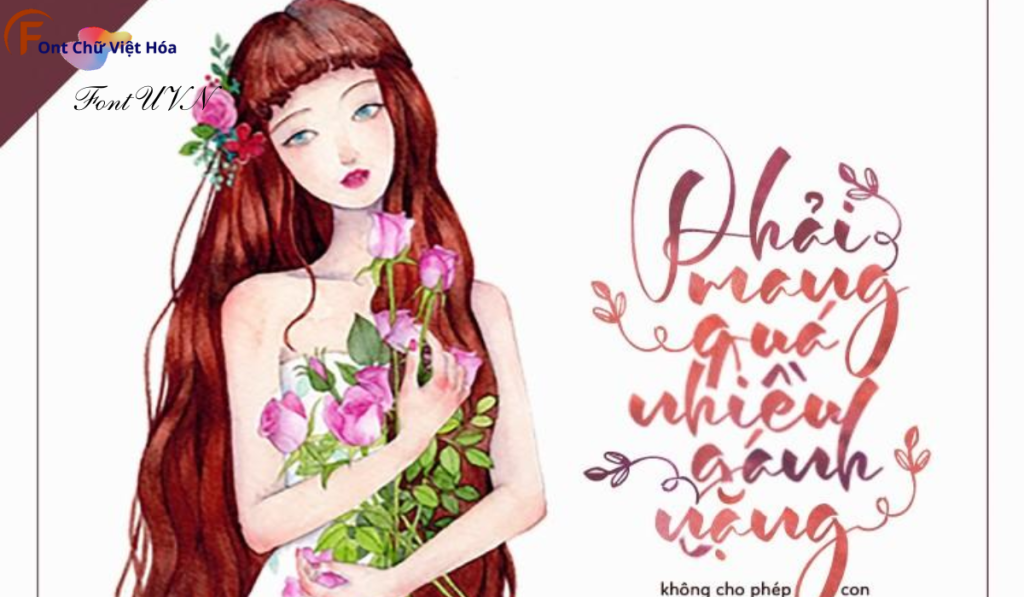
Font Chữ Thư Pháp UVN Việt Hóa
Tác giả: UVN Việt Hóa
Phân loại: Thư pháp, Nghệ thuật
Độ dày: Mỏng
Font Chữ Thư Pháp UVN Việt Hóa là một font chữ thư pháp nghệ thuật, thuộc bộ font UVN. Được thiết kế với mục tiêu mang lại sự mềm mại và thanh thoát, font này lý tưởng cho các dự án thiết kế như thiệp mời, logo, và bao bì sản phẩm. Với các nét chữ uyển chuyển và độ dày đều đặn, Font Chữ Thư Pháp UVN Việt Hóa không chỉ dễ đọc mà còn tạo cảm giác thân thiện và gần gũi. Việc Việt hóa font giúp người dùng dễ dàng sử dụng trong các thiết kế tiếng Việt, mang lại sự tiện lợi và thẩm mỹ cao.